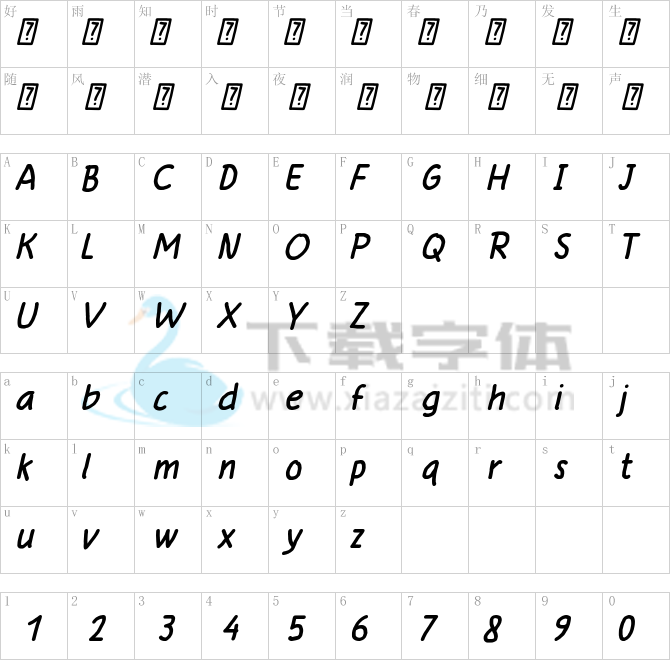
Anysome.otf字体下载,这款字体结构工整、笔画清晰,兼顾美观与易读性,适用于标题、正文、海报、包装、LOGO 等多种场景。字形优雅稳定,风格百搭耐看,适配日常排版与创意设计,让文字呈现更舒适、更具质感。Anysome.otf字体下载一笔一画,皆是细节,以均衡的比例、流畅的线条打造舒适视觉体验,字形端正大气,风格简约现代。无论是商业设计、品牌宣传还是日常排版,都能轻松驾驭,让文字更有格调与力量。Anysome.otf字体下载字体下载。